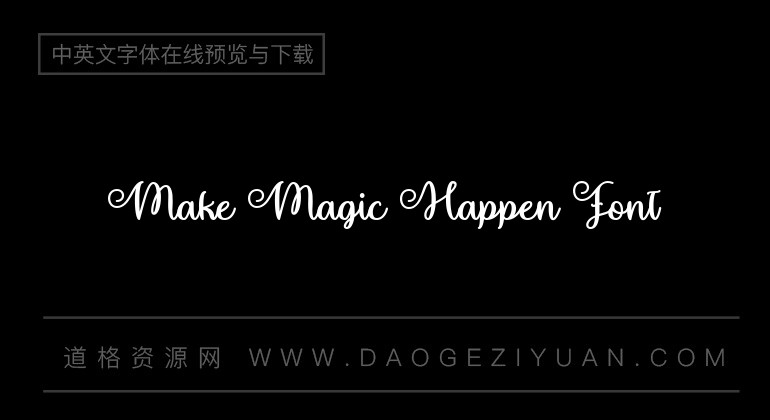
Make Magic Happen Font
Make Magic Happen Font 是一种手写风格的字体,创造出了一种神奇的氛围,适合用于许多不同的设计项目。 这种字体具有许多特点,如每个字母的形状都是独特的,且字母之间的间距非常适中,使得整个文本看起来非常平衡和和谐。此外,这种字体使用了一种粗体的笔画,使得文字看起来更加突出和引人注目。 Make Magic Happen Font 适用于许多不同类型的设计项目,包括海报、卡片、标志和包装设计。它非常适合想要传达有趣、轻松和神奇气氛的品牌或业务使用。
Make Magic Happen Font是一款非常不错的手写艺术字体,具有很好的视觉感,适合于文化类的宣传设计、商业类品牌的广告和产品包装设计以及个性化文字排版等较多场景。